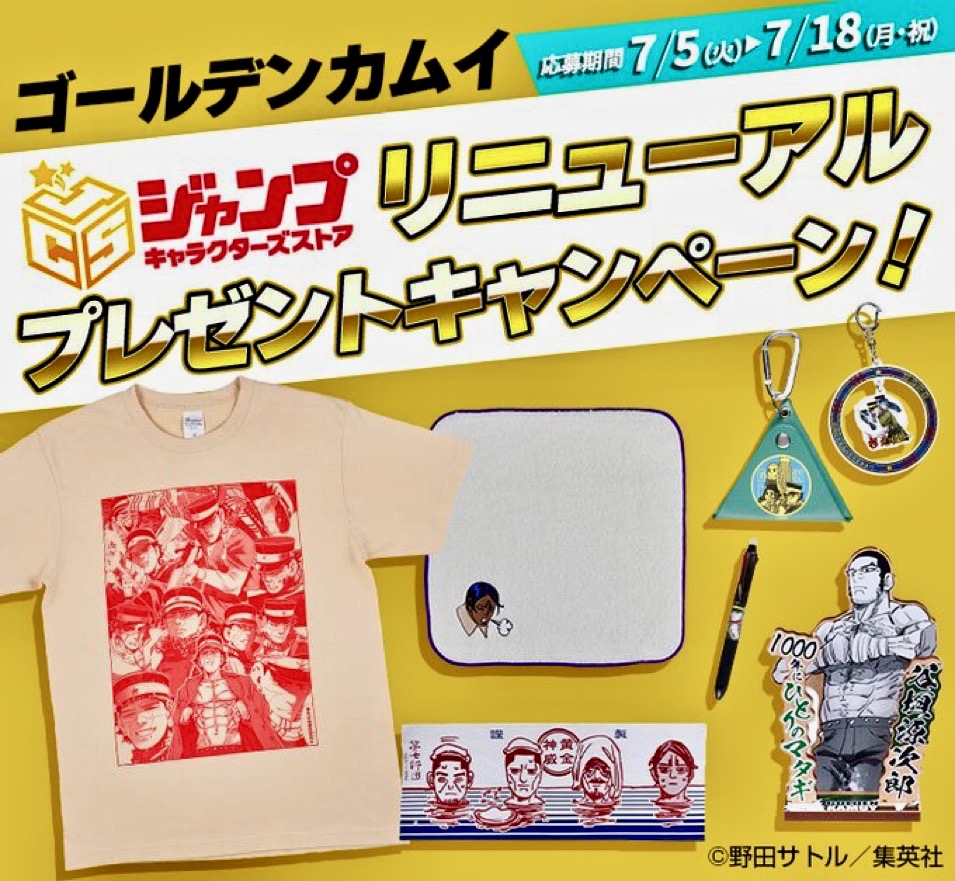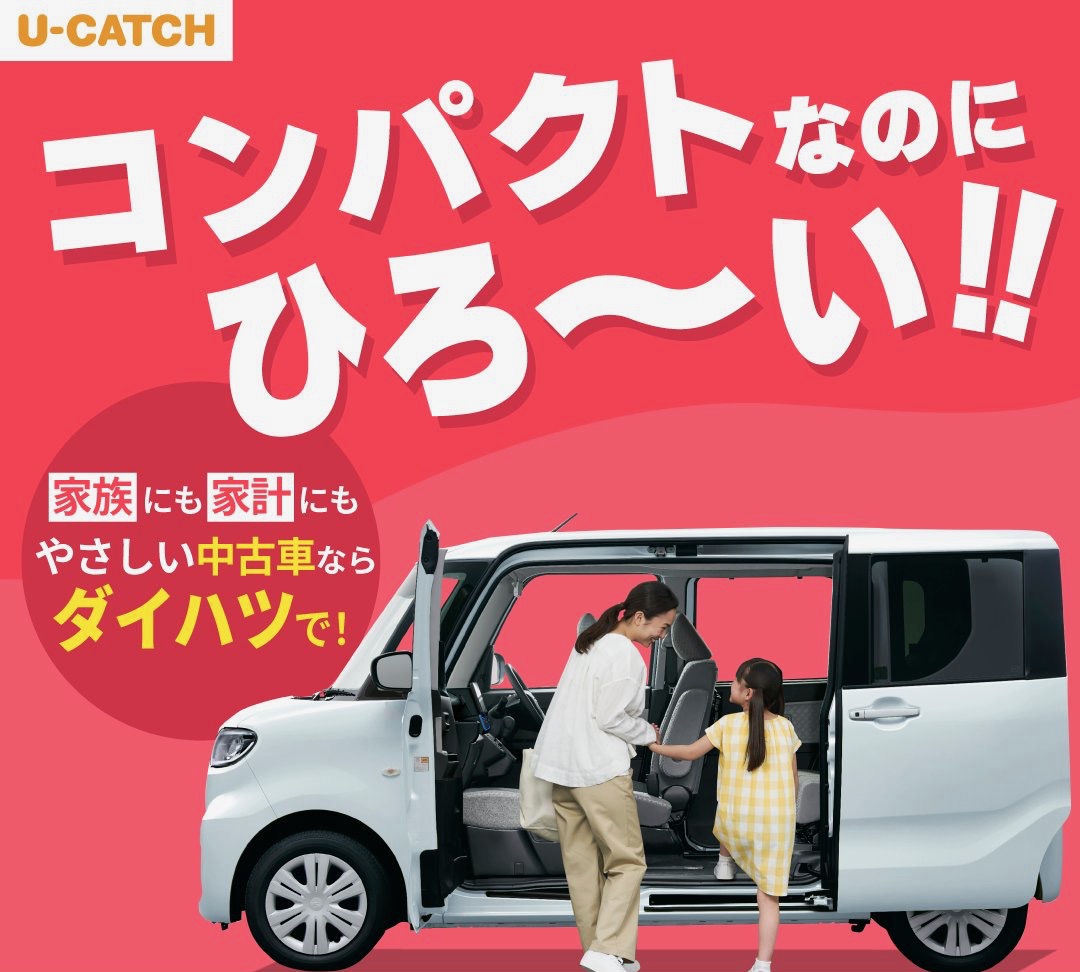
和食さとのCM  takumi  2024年12月17日(火) 18:44  HP
放映中の和食さとのCMで「ルイカ-09」が使われています。
これは今年7月頃のCMより。
ルイカが継続して採用されているようですね。
この書体、すこしずつ使用例が増えてきて嬉しいです!
ローソンのパン  みきお  2024年12月13日(金) 21:17
ローソンのパンの商品名に、ルイカフォントが使用されていました。
おそらくAdobe Fontsによるものと思われます。
こちらは別の商品。
確かにルイカフォントですね。
ただし、現在Adobe Fontsに提供しているウェイトとは違うようです…。
モノピン太字でした!  さとうゆたか  2024年12月15日(日) 9:56 [修正]
みきお様、やはりAdobeFontsのようです…。
使われているフォントは「モノピン太字」のようです。
このフォントの和文部分には「ルイカ05」が使用されています。
欧文「!」のデザインで気づきました…。
Youtubeのサムネ画像  さとうゆたか  2024年11月17日(日) 10:37
08ウェイトかな…。
これも…。
英数字でルイカ系フォントと分かる。
Xで見つけた  さとうゆたか  2024年9月24日(火) 21:41
「好きなフォントはルイカ」と公言する、生ハム帝国🖥動画編集講師さんのツィートに使われた画像。
プールの広告  さとうゆたか  2024年8月2日(金) 6:37
東武スーパープール。
これは、駅で見たポスター。
アニメの劇中  takumi  2024年7月29日(月) 23:38  HP
放送中のアニメ『【推しの子】』第14話「リライティング」より。
「シュワっとはじける!」の文字がルイカですね。
Adobe Fontsの影響すごいなぁ…。
あいかわらず、画面の隅々までよく見てますね!
タイプラボのフォントは、全角の感嘆符がナナメなので判りやすいかな。
ここぞ!という時に…  takumi  2024年3月17日(日) 23:29  HP
深夜にJ:COMチャンネルで見かけたCMでルイカが使われていました。
人気商品…なんですかね(笑)。
最後にこれも。
ルイカ書体、かなり見かけるようになってきましたね…。
イオンのキャンペーンチラシ  takumi  2024年2月15日(木) 18:31  HP
イオンのキャンペーンチラシで「ルイカ」が使われていました。
上の「証券診断で〜」とか、真ん中の「おみくじの〜」のところですね。
これは下記ページに掲載されていたバナー。
AdobeFontsでしょうかね?
ここにライセンスした影響は大きいですね。
カレンダーの表紙  さとうゆたか  2024年2月14日(水) 9:57
さいとう・たかを 劇画日めくりカレンダー。
「さいとう・たかを」の部分。
表紙は違うが、中身は同じらしい。
テレビユー福島の「Nスタふくしま」という番組のEPGの画像に、ルイカが使われていました。
(一部しか写っていません)
福島県で見られる番組なんですね、貴重です!